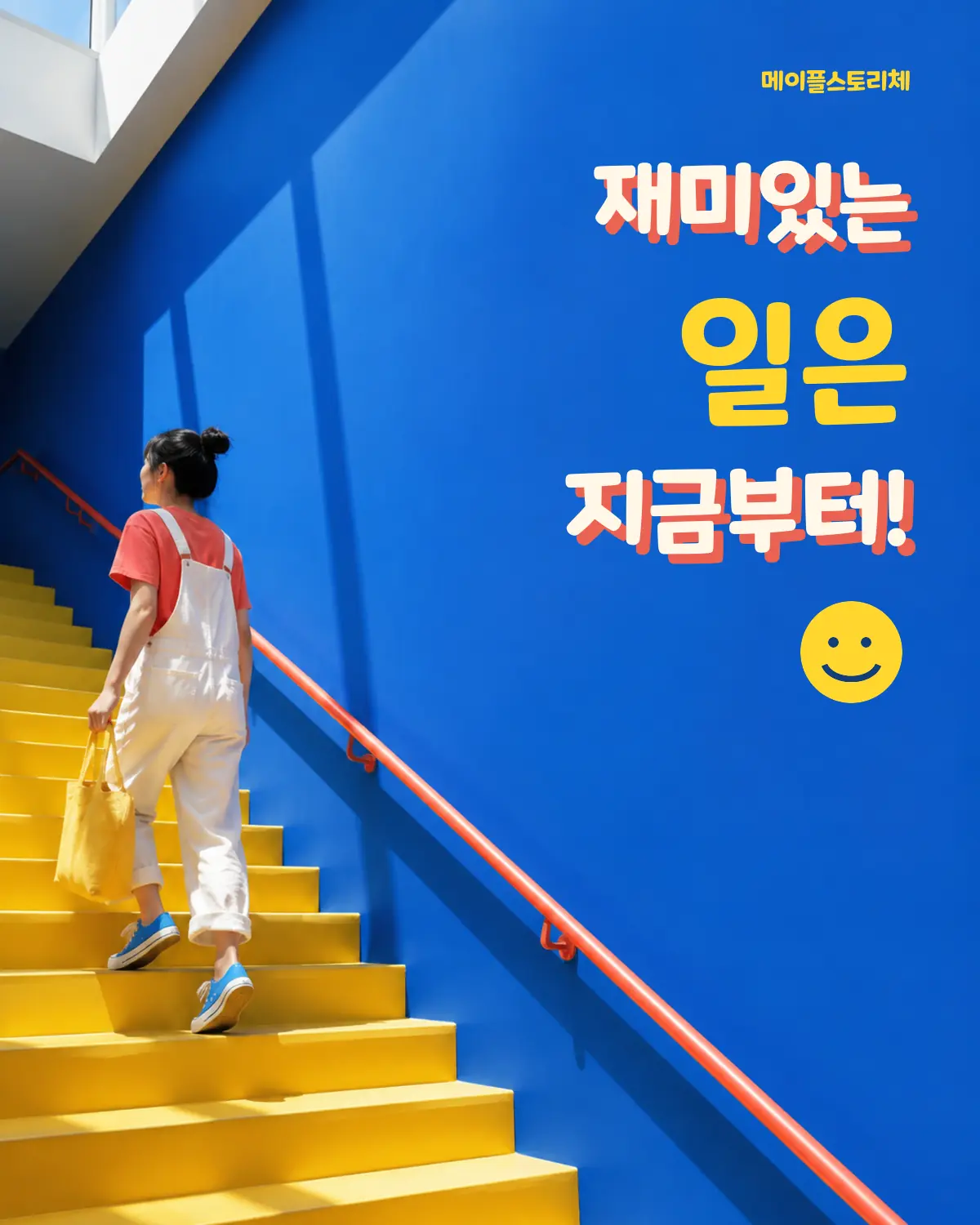
메이플스토리 — 넥슨에서 배포하는 무료 폰트입니다. 둥글고 굵은 자형에 귀여운 캐릭터성을 더해 밝고 경쾌한 인상을 주는 디스플레이 서체
넥슨이 2017년 한글날에 무료로 공개한 서체입니다. 메이플스토리 특유의 귀엽고 발랄한 캐릭터와 유쾌한 게임 분위기를 반영했다고 알려져 있습니다.
넥슨이 직접 쓴 조형 설명은 따로 공개돼 있지 않아 형태는 파일을 보고 적습니다. 획이 둥글게 다듬어져 있고 자소가 통통해서, 게임 화면에서 아이들이 읽기 좋게 만든 서체의 성질이 드러납니다.
굵기는 Light와 Bold 두 가지입니다. 아동이나 게임 관련 콘텐츠, 캐주얼한 캐치프레이즈에 어울리고 격식 있는 문서에는 맞지 않습니다. 무료로 상업적으로 쓸 수 있지만 넥슨 서체 공통으로 수정이 금지되어 배포된 형태 그대로 써야 합니다.